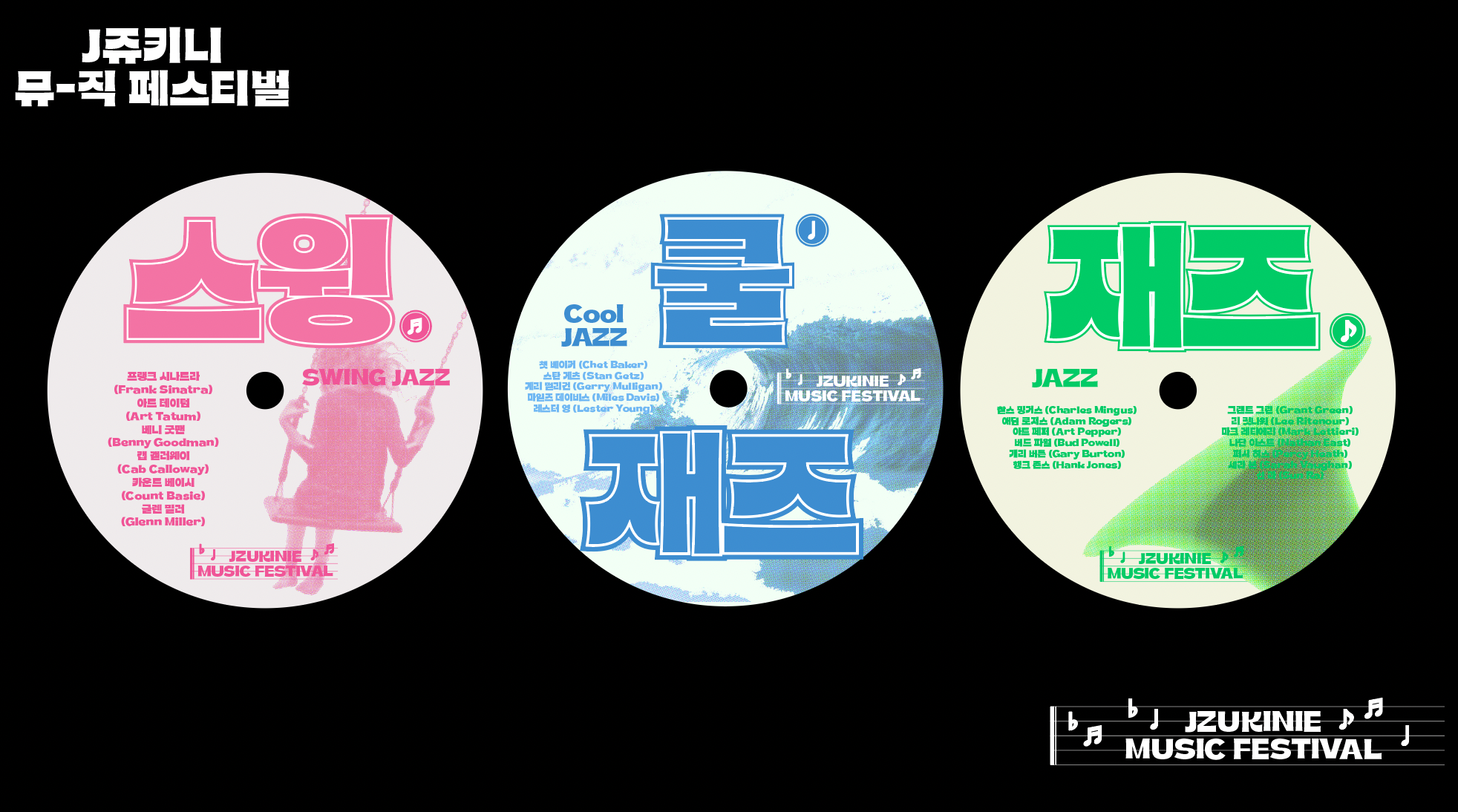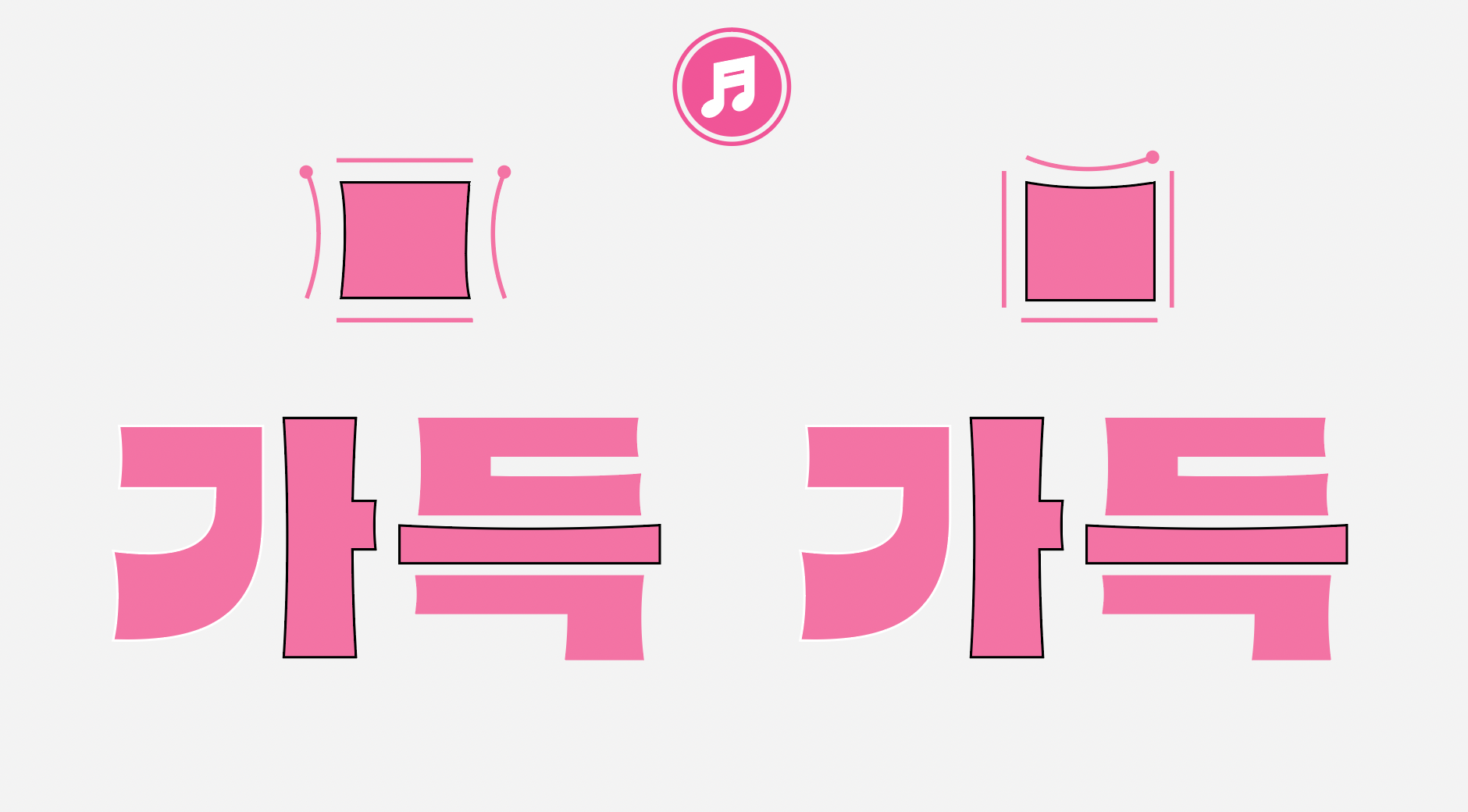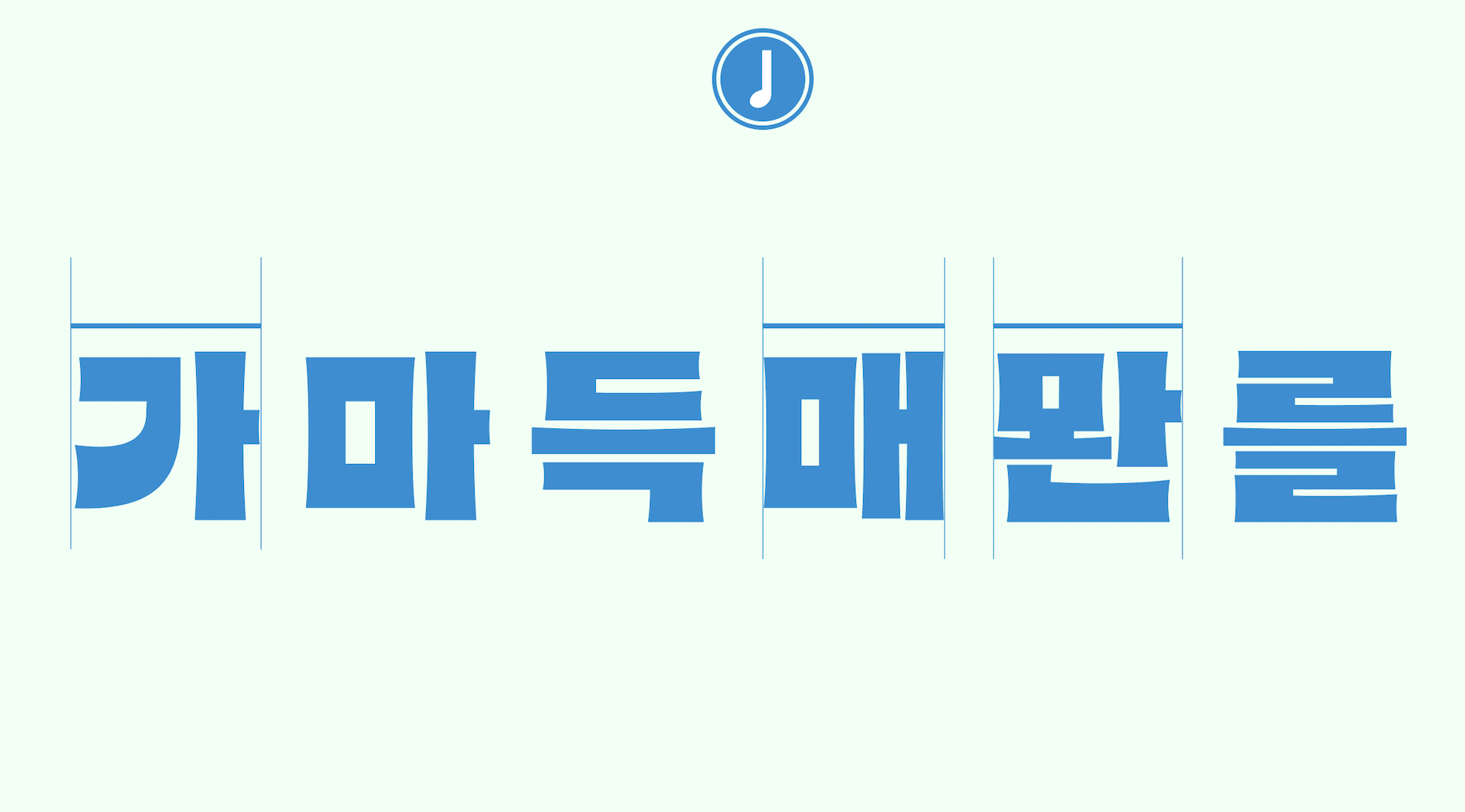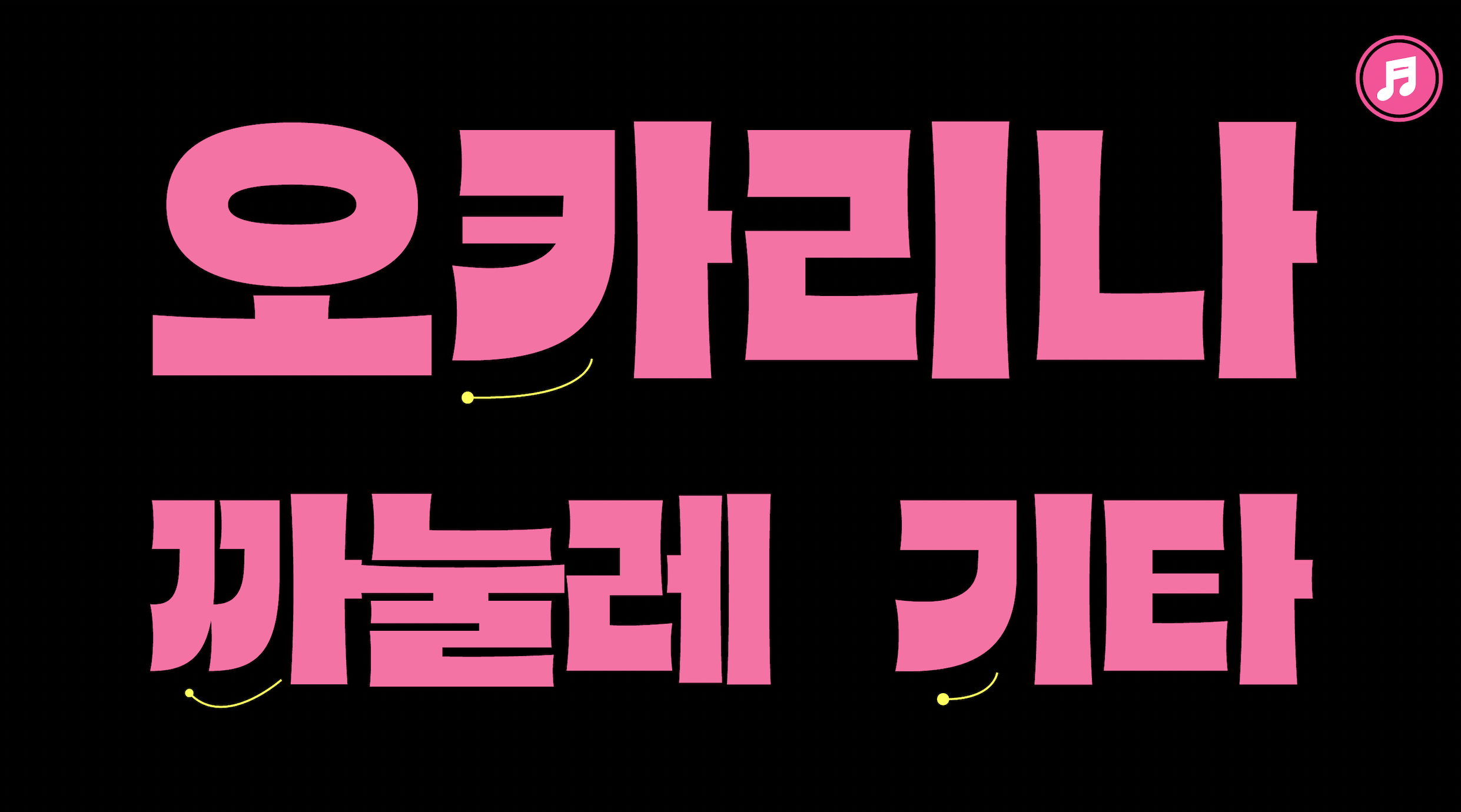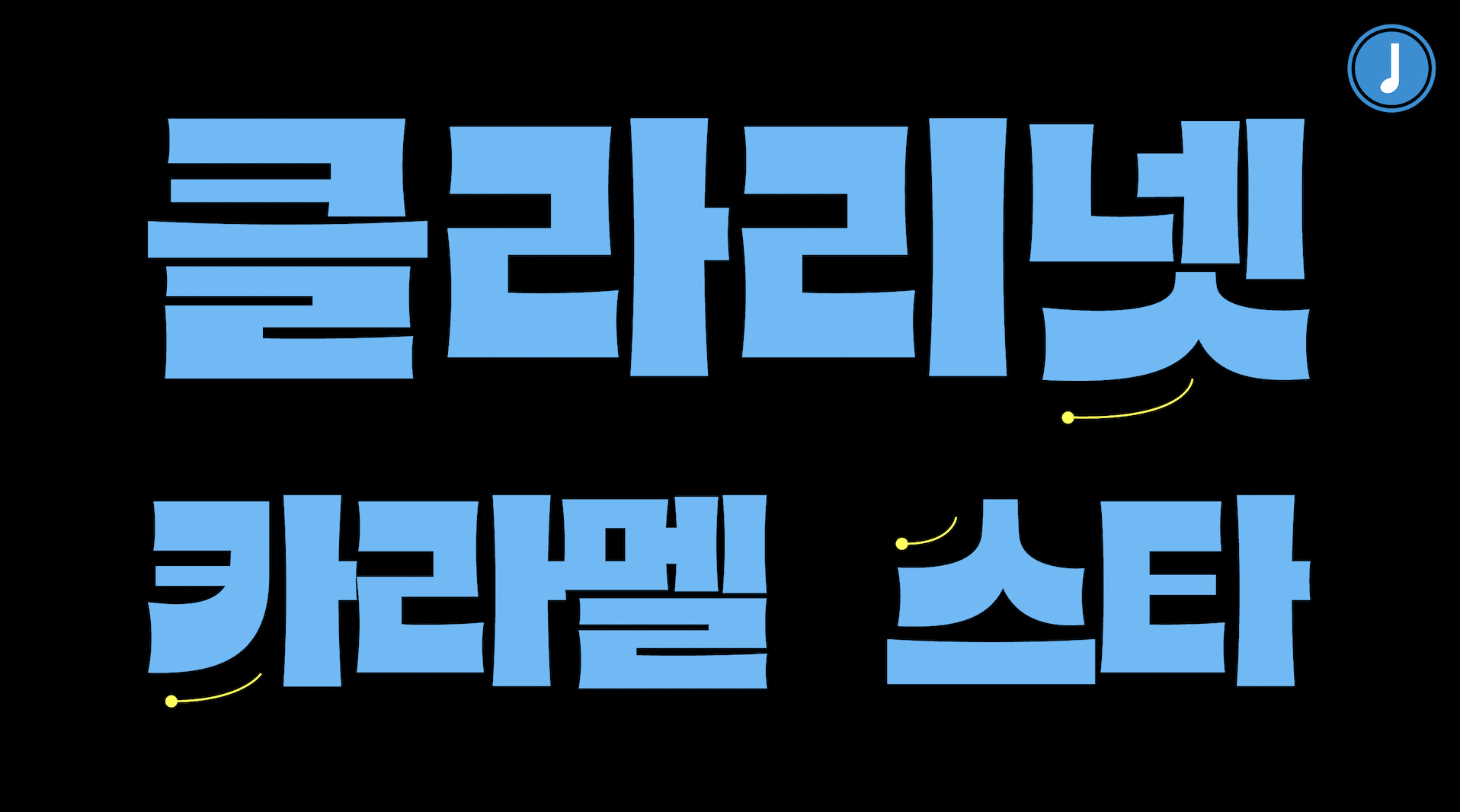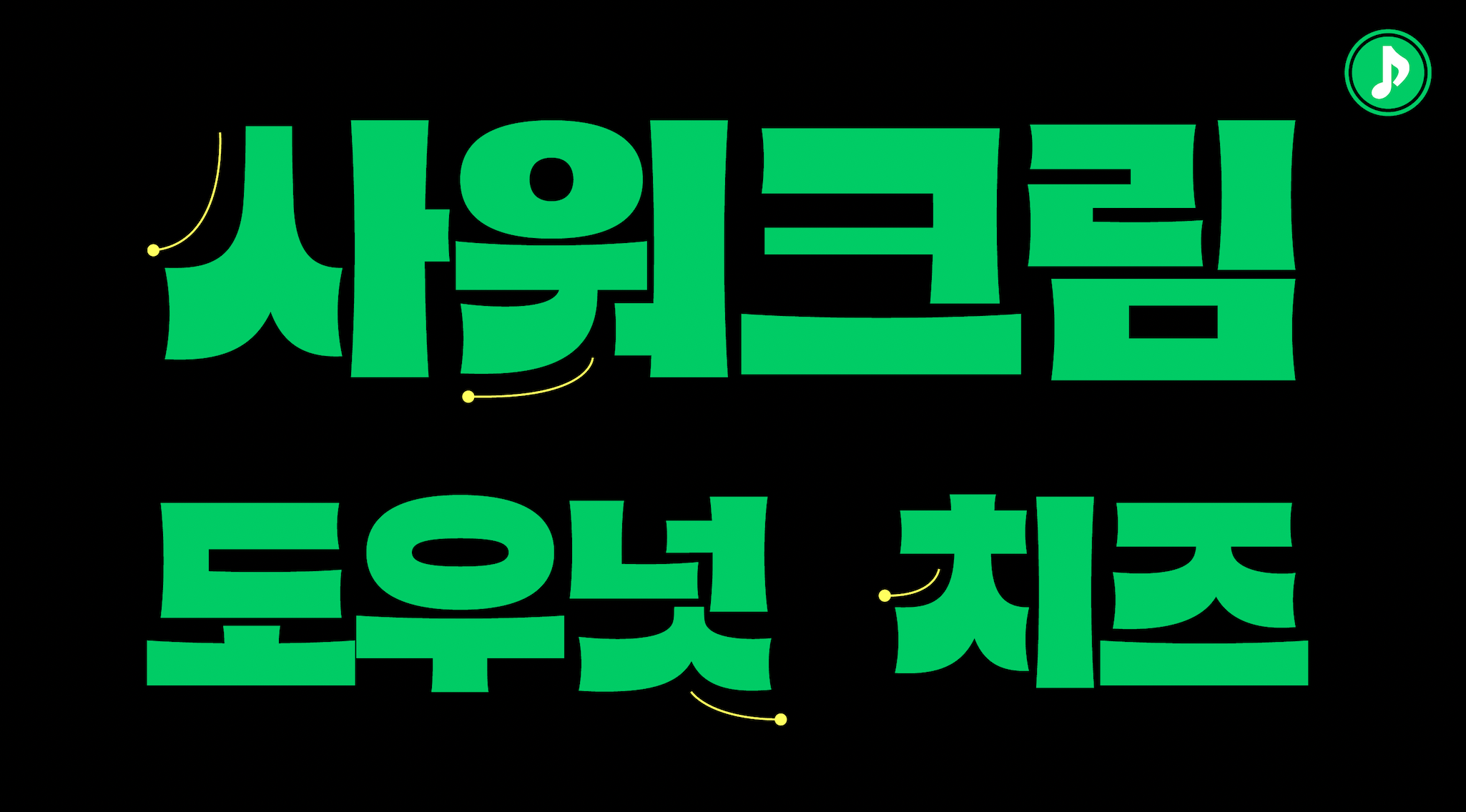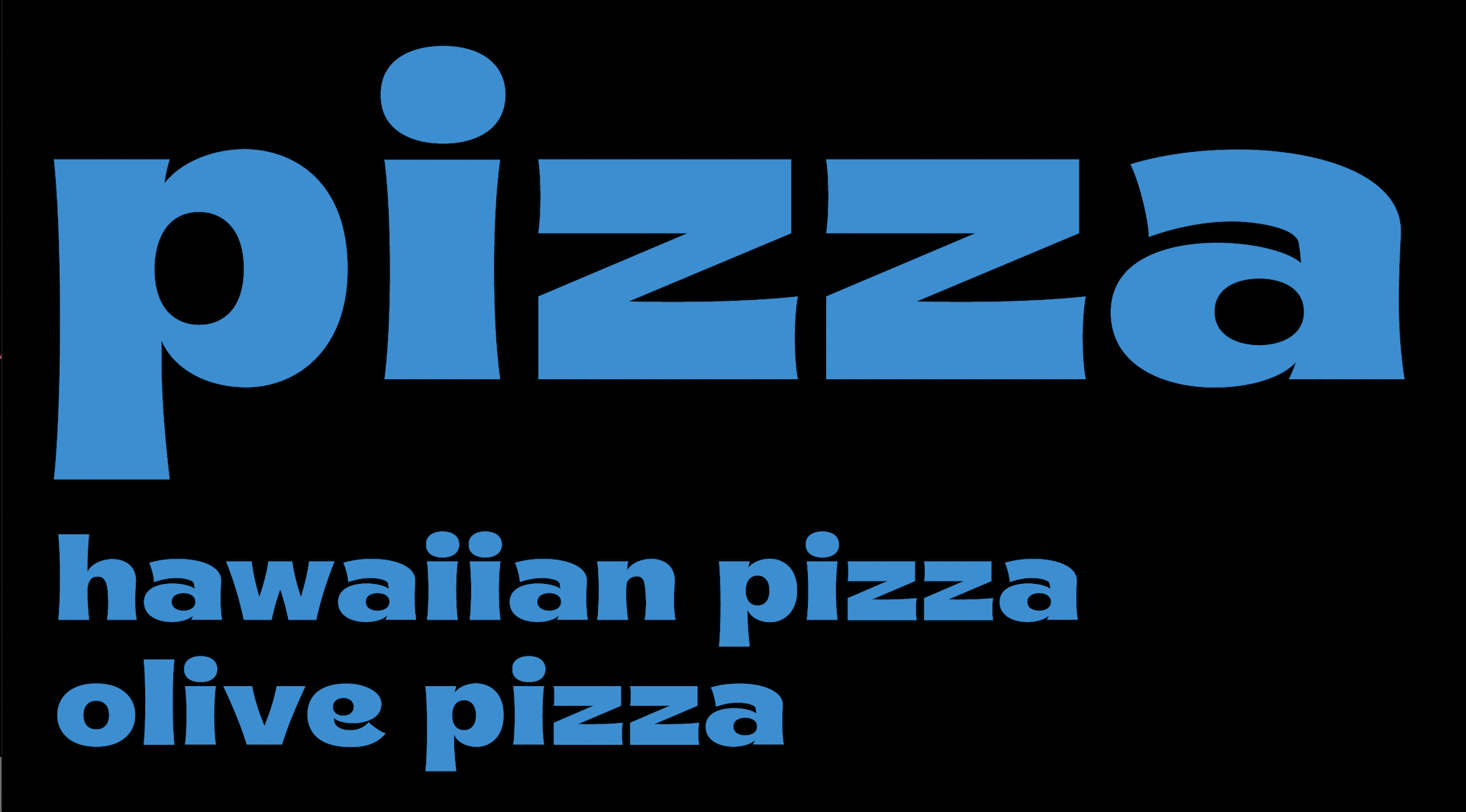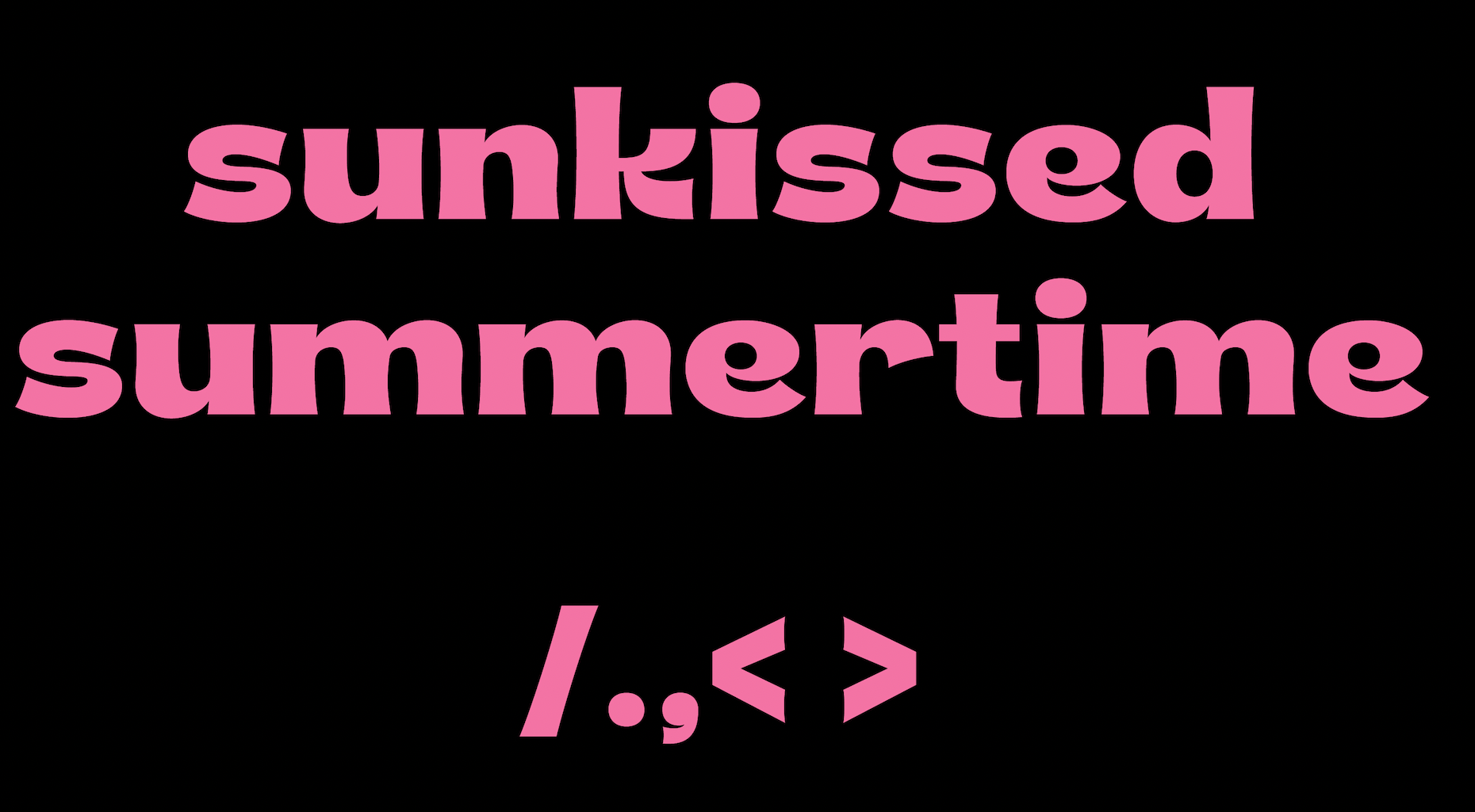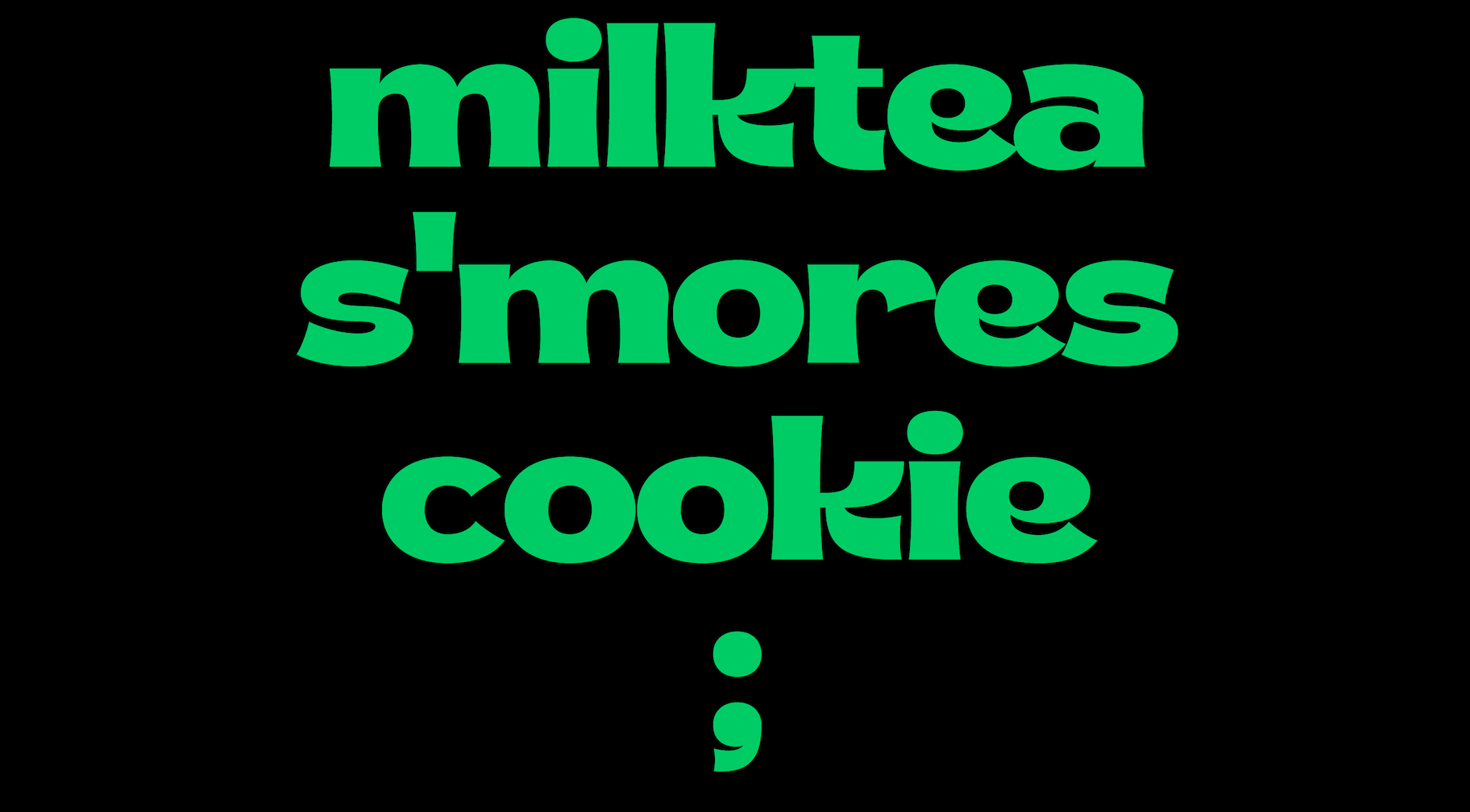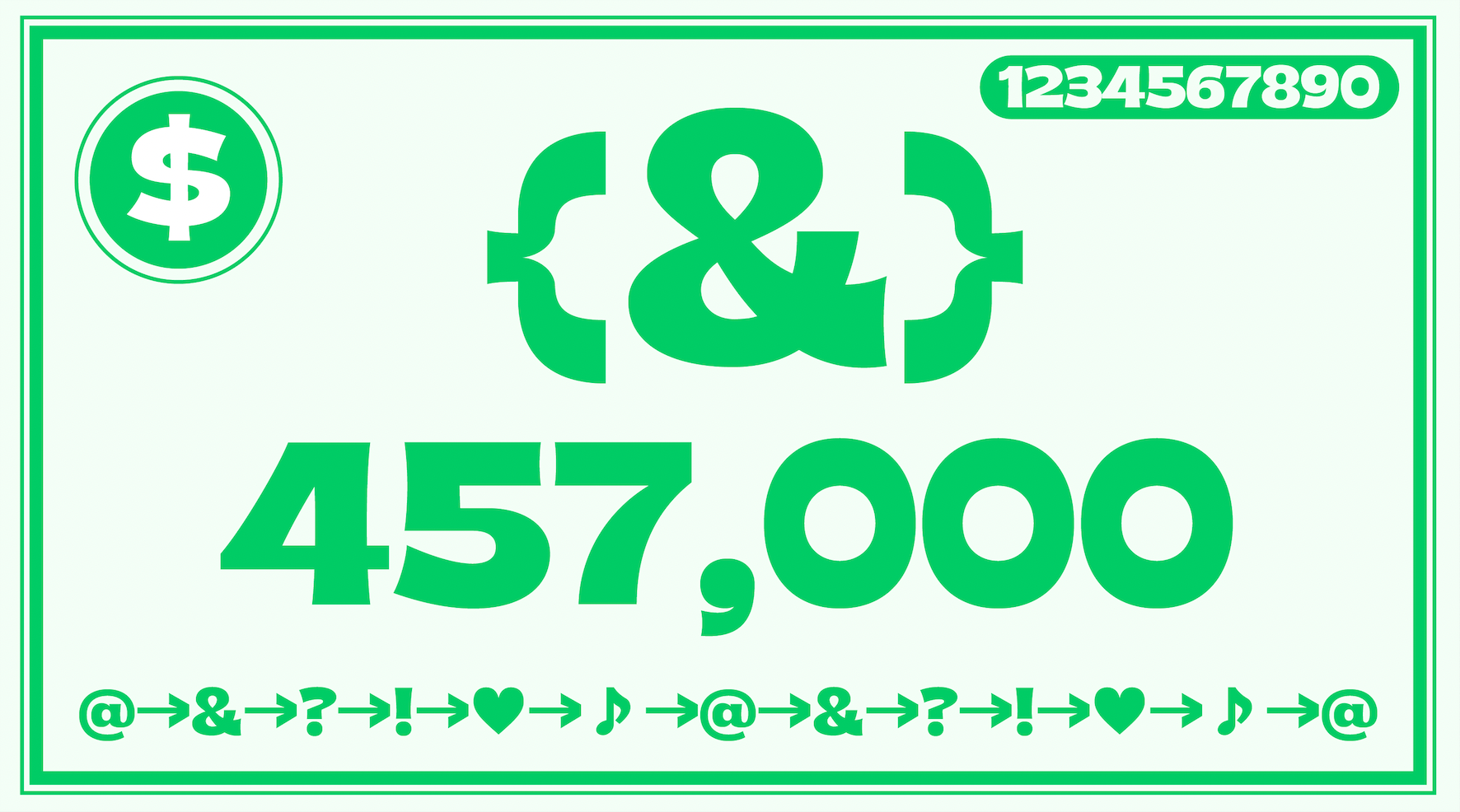
J쥬키니는 네모틀 안에 꽉 채운 자소와 두껍고 단단한 획으로 무게감이 느껴지는 헤드라인 서체입니다.
J쥬키니는 강한 주목도와 개성, 트렌디함을 보여주는 Black 굵기의 그래픽체로 아주 큰 사이즈에서부터 부제목용 사이즈까지 모두 활용할 수 있습니다.
이번 가을 새로 등장하는 J쥬키니를 음악과 함께 풀어냈는데요.
재즈와 함께 어우러진 쥬키니를 만나보세요!
(아참! 쥬키니가 애호박이라는거 아시나요?)
애호박(쥬키니)처럼 단단하고 과감하게 휘어진 곡선과 획의 특징을 찾아보세요. :)
🎶 한글 디자인 특징
1> 획: J쥬키니는 획의 오목한 면과 강, 중, 약의 획대비가 흥미롭게 표현된 서체로써 각 모임꼴별 변화하는 획 두께에 주목해주세요! 특히 민글자에서 받침글자로 갈수록 획의 강약 대비가 더욱더 강해지도록 모듈화했습니다. 이는 획이 많아지는 글자 안에서 공간의 분배와 획대비의 컨셉을 효과적으로 유지할 수 있으며 동시에 글자끼리 서로 무게감 차이를 최소화할 수 있습니다.
2> 자소: J쥬키니는 개성있는 자소디자인이 특징입니다. ㅅ,ㅈ,ㅊ (ㅆ,ㅉ)의 비대칭 디자인과 ㄱ,ㅋ,ㅟ, ㅝ 과감하게 뻗어가는 곡선 획이 특징입니다. ㅆ, ㅉ의 경우 두껍게 뻗어가는 곡선을 더 강조하기 위해 쌍자음의 왼쪽 자음의 내리점을 과감히 생략했습니다.
🌈라틴 디자인 특징:
‘ㄱ, ㅅ’의 빗침과 ‘ㅟ’의 짧은 기둥에서 보이는 곡선으로 두껍게 뻗어가는 획을 K, Q, R 에서 표현했고, 전체적으로 강, 중, 약 획대비를 살려 한글과 통일성을 가져갔습니다.
🤟🏻숫자 및 글리프 디자인: 한글디자인의 통일성을 살린 숫자와 기호를 생각하며 디자인했습니다. 숨은 추가글립이 있는데요, 기본형 '&' 과 함께 추가로 제작된 개성있는 '&' 도 찾아보세요 :)